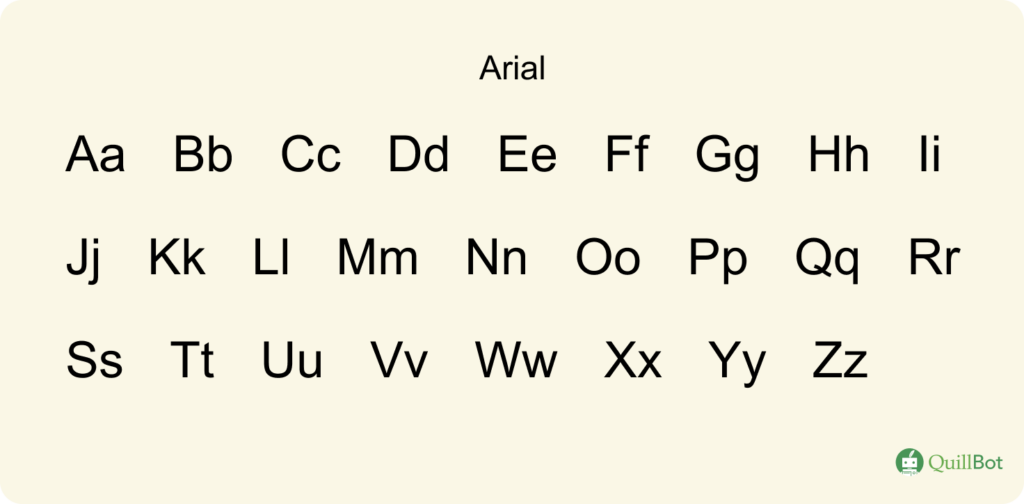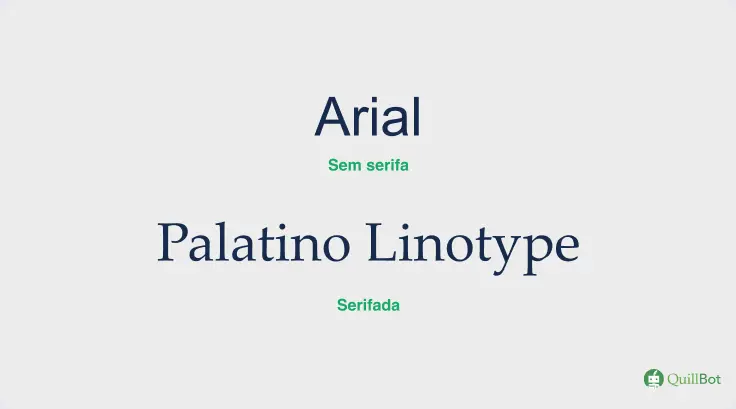
Arial | Usos e história
Qualquer designer gráfico experiente dirá: encontrar a fonte certa exige conhecimento e um senso estético que não se inventam.
A tipografia pode influenciar significativamente a legibilidade e a acessibilidade da mensagem transmitida. Ela também pode reforçar a linha editorial de uma marca, refletindo sua identidade e reputação junto ao público em geral.
As fontes tipográficas podem assumir muitas formas, podem ser lúdicas ou funcionais, finas ou grossas, arredondadas ou lineares.
Entre os grandes clássicos do gênero, integrados de forma padrão em quase todos os softwares de processamento de texto, encontramos a fonte Arial.
- Ano de criação: 1982
- País de origem: Estados Unidos
- Criadores: Robin Nicholas e Patricia Saunders (tipógrafos da Monotype Imaging)
- Tipo de fonte: linear
- Tipo de serifa: sem serifa
- Classificação de Thibaudeau: antigo
- Popularidade: ++ (amplamente utilizado, pois está presente por padrão no Windows, mas não muito popular entre designers gráficos)
- Imagem transmitida: funcional, universal, básica.
- Ponto de atenção especial:
- Originalmente concebida como uma alternativa de baixo custo à Helvetica.
- Otimizada para impressão a laser de baixa resolução.
Arial é uma das fontes mais famosas, senão a mais conhecida de todas. Definida como padrão em muitos processadores de texto, incluindo o Google Docs, ela ainda é amplamente utilizada, apesar da crescente antipatia dos designers por ela.
Fonte Arial: história e desenvolvimento
Arial é, antes de tudo, uma questão de economia excessiva.
No início da década de 1980, a fonte Helvetica estava no auge de sua popularidade.
A sua popularidade se devia não apenas às suas linhas limpas e simples, que a tornavam ideal para diversos fins, mas também à sua excelente qualidade de impressão.
Ou seja, os designers gráficos que optam por essa solução têm certeza de que o resultado físico estará à altura da forma digital, sem erros de espaçamento entre letras ou outros contratempos que poderiam arruinar semanas de trabalho.
Ao desenvolver seus primeiros sistemas Windows, a Microsoft obviamente tinha em vista essa joia da tipografia funcional, mas um problema surgiu rapidamente: a Helvetica era licenciada e era preciso pagar uma taxa substancial aos detentores dos direitos autorais para usá-la.
Assim, a Arial foi concebida e projetada como uma substituta da Helvetica.
Mesma largura de letra, mesmas quebras de linha… a semelhança é tanta que, à primeira vista, é difícil notar a diferença entre as duas.
Dessa forma, os processadores de texto exibiam corretamente documentos originalmente projetados para Helvetica, mas com um custo menor.
A ironia dessa história é que hoje o nome Arial é mais conhecido que o de Helvetica, dada a popularidade do Windows e a revolução informática que aconteceu no mundo ocidental a partir do final da década de 1990.
Ao contrário da Helvetica, criada numa época em que as fontes eram concebidas principalmente para serem lidas em papel impresso, a Arial foi otimizada desde o início para ser mais visível do que o seu modelo em telas pixelizadas, e isso em diferentes resoluções.
Arial: um clássico entre os clássicos
Arial (assim como suas variantes Arial Black, Arial Bold, Arial Narrow , Arial Rounded, Arial Light, Arial Medium, etc.) é uma fonte tipográfica descrita como sem serifa, ou linear.
E essas características têm um impacto significativo na forma como é percebida pelos leitores!
Arial é uma fonte sem serifa, também chamada de fonte linear.
- As fontes serifadas possuem pequenos “pés”, ganchos ou traços decorativos nas extremidades dos caracteres. Elas evocam imediatamente um design clássico e sério, conferindo à comunicação um caráter institucional e simbolizando certa autoridade. São amplamente utilizadas em editoras e mídias impressas, pois são consideradas mais adequadas para a leitura de textos por períodos prolongados.
Exemplos de fontes serifadas incluem: Baskerville, Garamond, Palatino Linotype e Times New Roman. - Já as fontes sem serifa não possuem serifas. Suas linhas são retas e limpas. Elas têm uma aparência moderna e minimalista; seu design é limpo, porém acessível. São frequentemente usadas na web devido à sua legibilidade otimizada para telas e ao seu impacto visual.
Exemplos de fontes sem serifa incluem: Calibri, Futura, Helvetica, Open Sans, Roboto, Tahoma.
A Arial se apresenta objetivamente como uma representante digna das fontes sem serifa.
Com silhueta simples, estabilidade na tela, design neutro e reconhecida legibilidade, é ótima quando se trata de interfaces web e mensagens impessoais.
Além disso, não perde nenhuma de suas qualidades quando reduzida a um tamanho pequeno; uma vantagem rara o suficiente para merecer destaque. Reduzir uma fonte cursiva ou decorativa abaixo de 8 representa uma significativa perda de legibilidade.